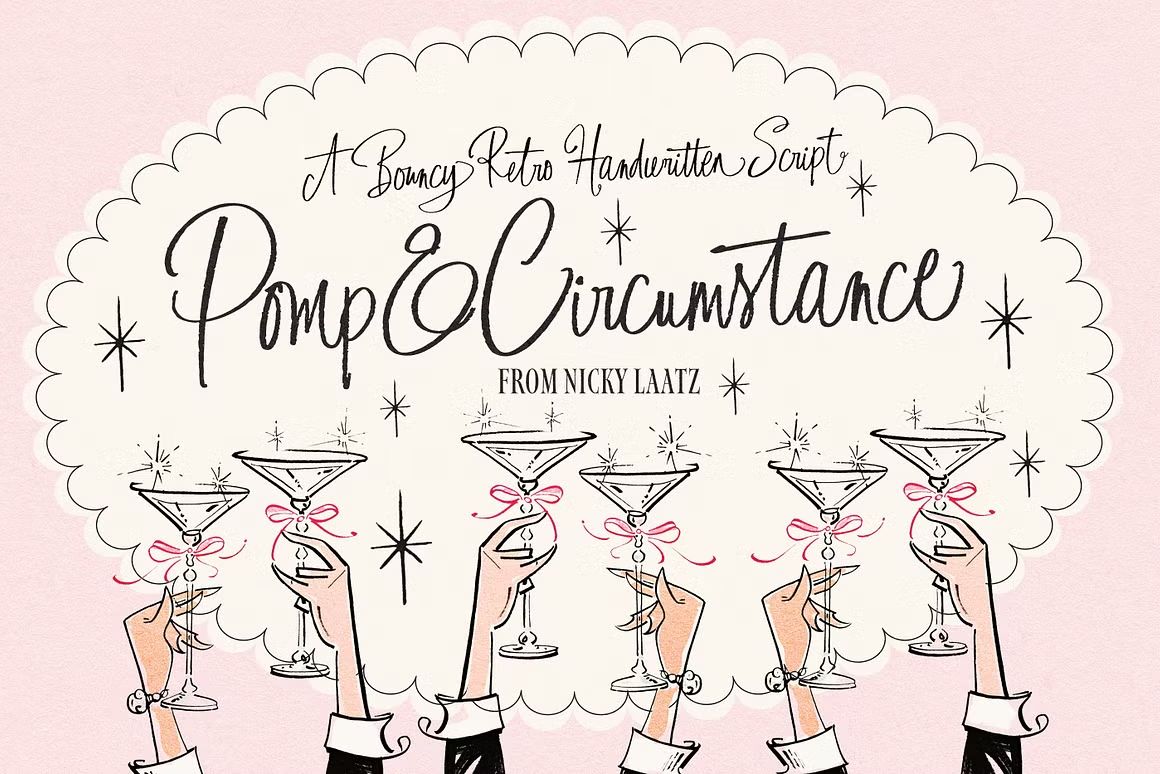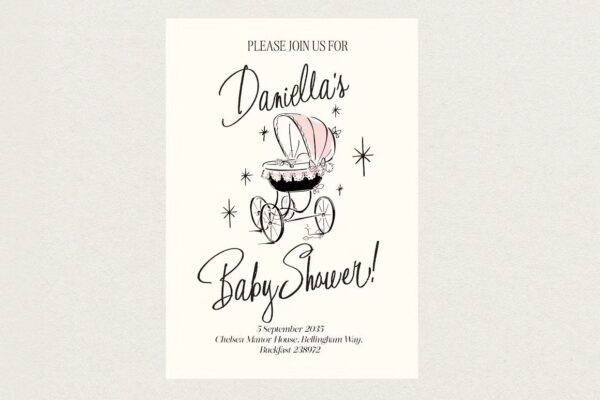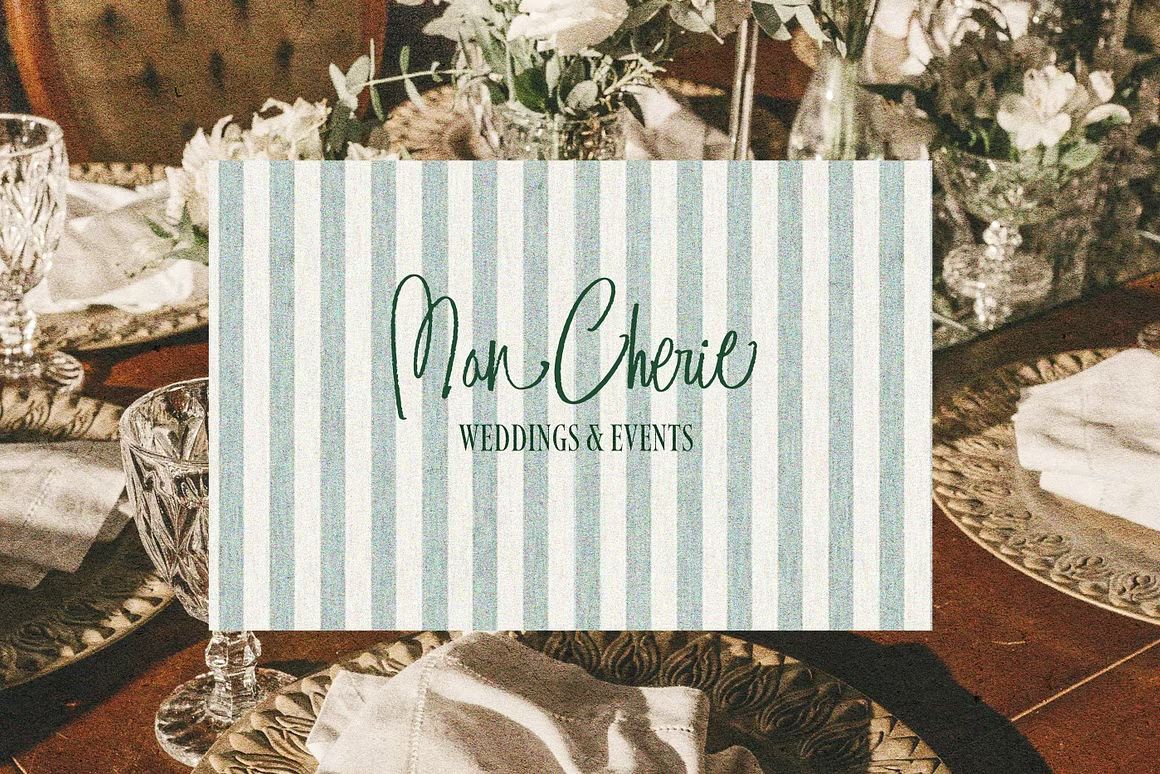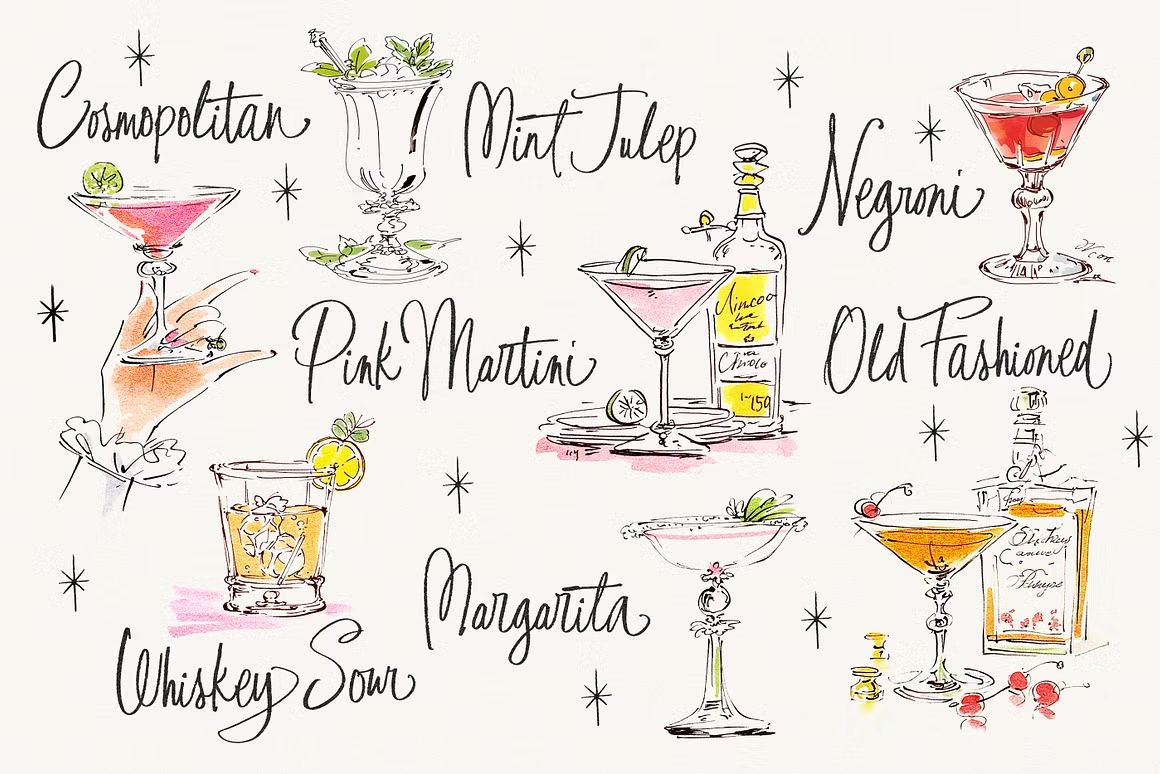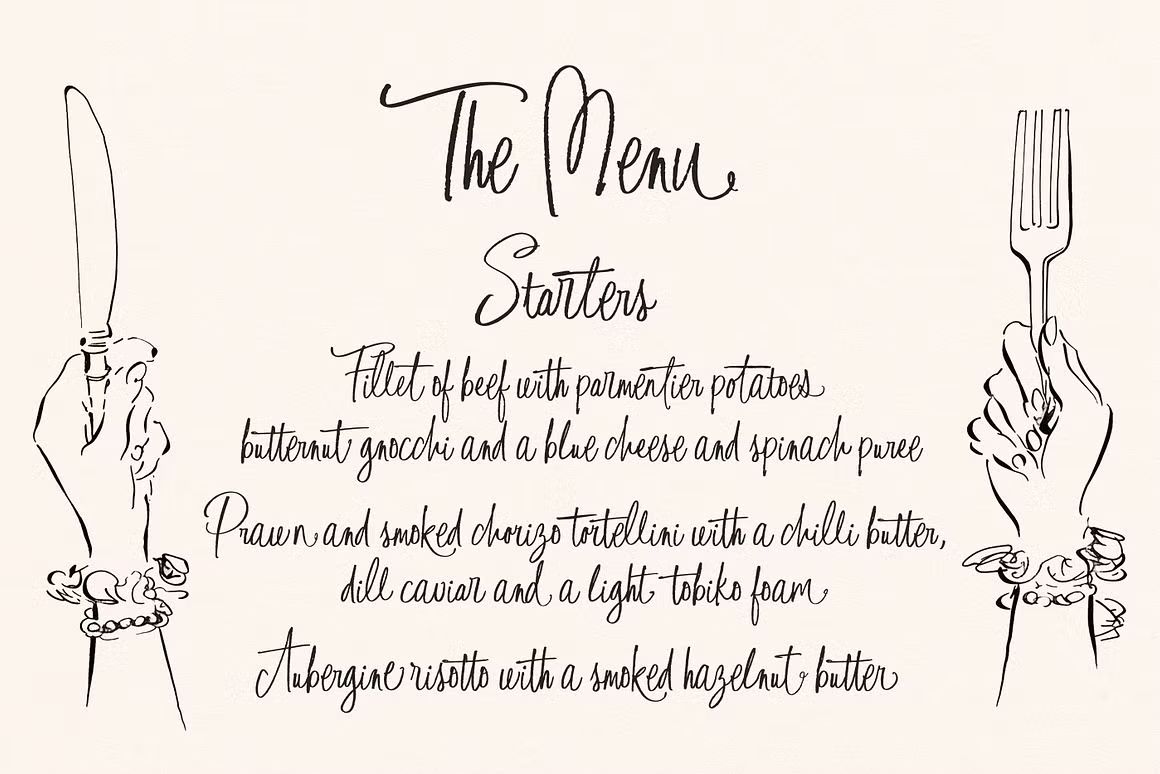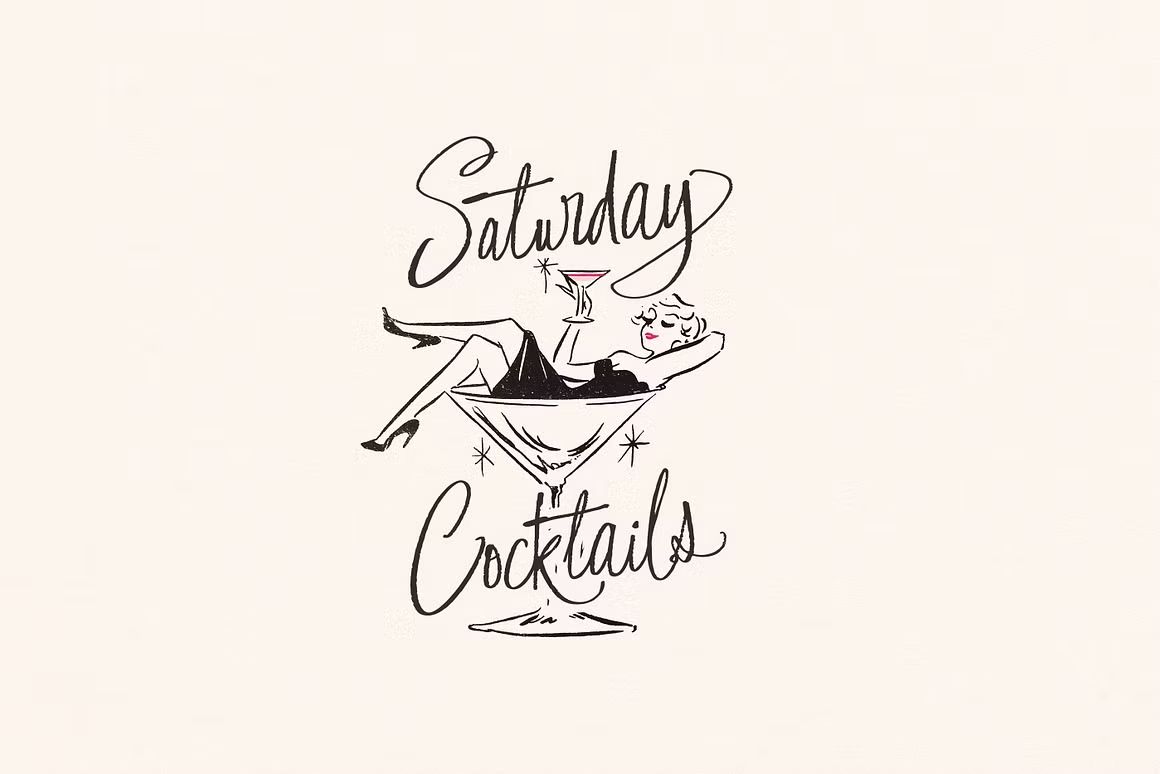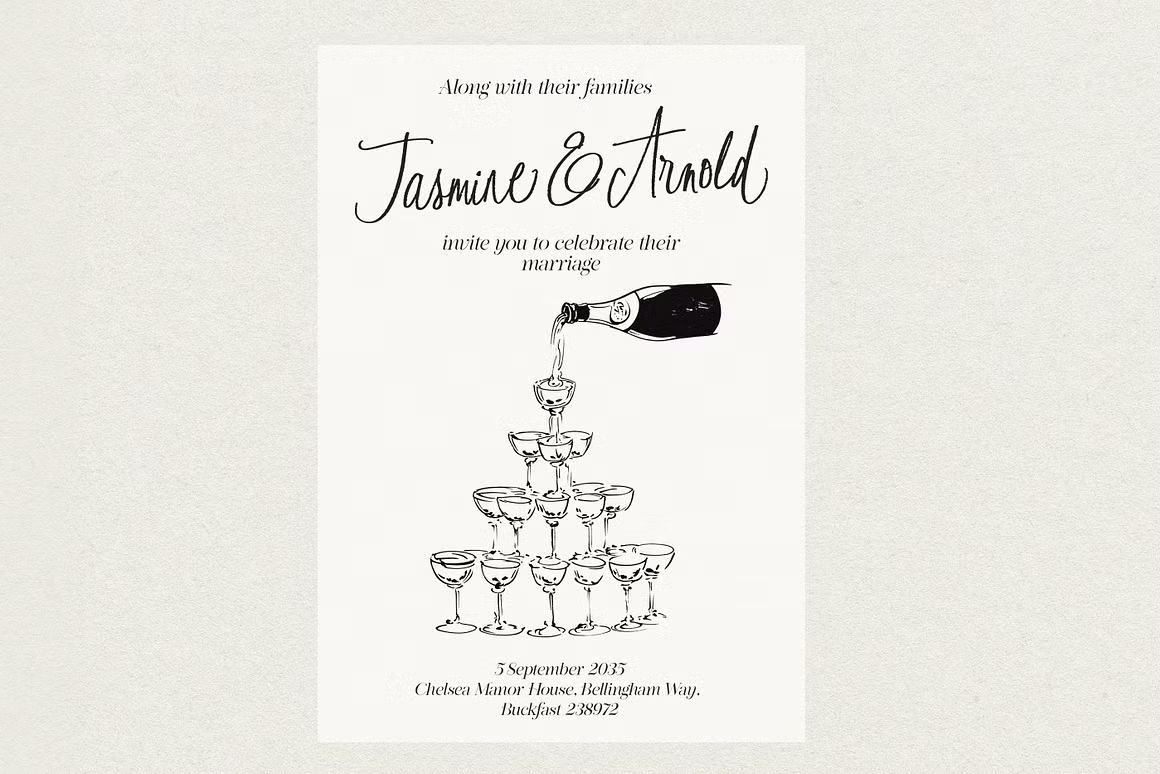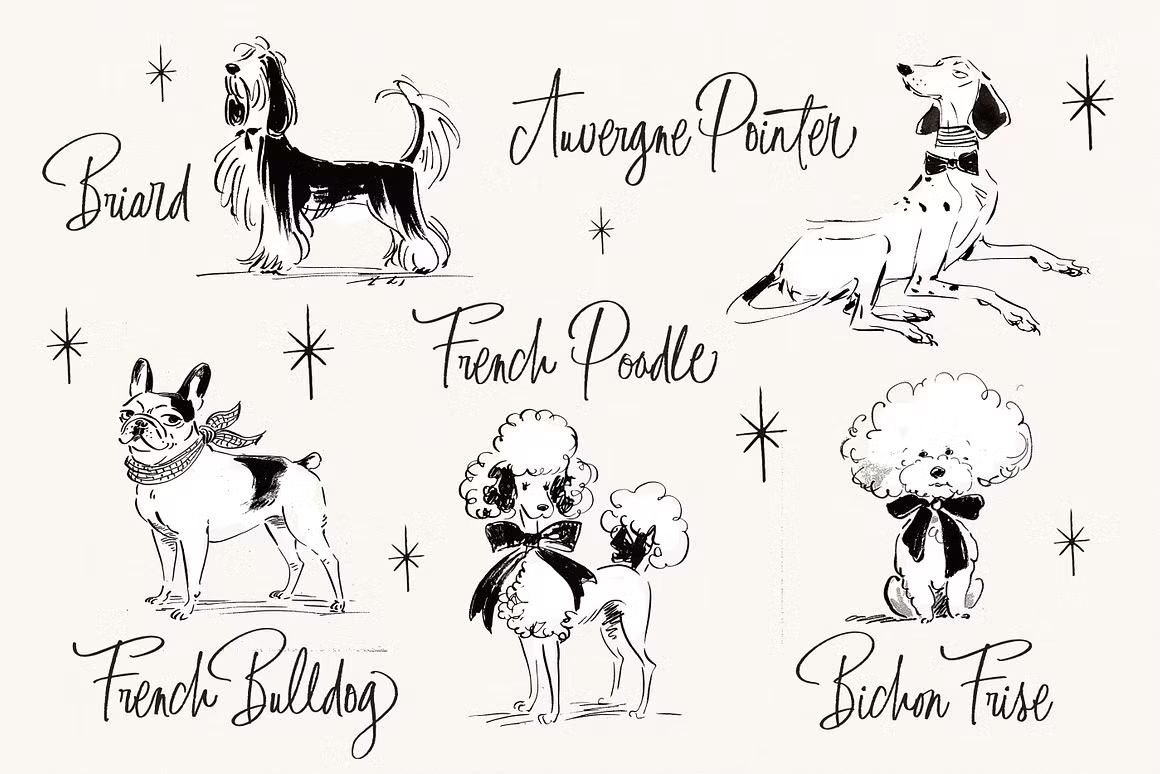
Pomp & Circumstance – Script Font
Pomp & Circumstance adalah font script elegan dengan desain tulisan tangan yang mewah dan artistik, cocok untuk undangan, branding, logo, dan proyek kreatif yang membutuhkan kesan formal dan sofistikated.
Pomp & Circumstance adalah font script elegan yang memadukan kehalusan dan kemewahan dalam setiap lekukannya. Dengan gaya tulisan tangan yang artistik, font ini sangat cocok untuk undangan pernikahan, logo, branding, kartu ucapan, dan proyek desain lainnya yang membutuhkan nuansa formal dan sofistikated.
Fitur unggulan:
• Gaya script elegan dengan desain tulisan tangan yang mewah
• Cocok untuk undangan, logo, branding, dan kartu ucapan formal
• Termasuk huruf besar, huruf kecil, angka, dan simbol lengkap
• Ideal untuk proyek cetak maupun digital yang membutuhkan kesan formal dan elegan